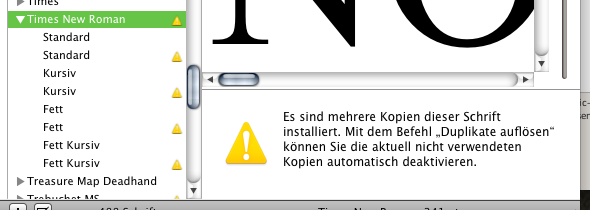
Zeilenhöhe Times New Roman vs. Doulos SIL
Die TNR einfach durch die Doulos zu ersetzten hab ich grad kurz versucht, das fällt aber auf, weil die TNR ein g mit Kringel (hat das nen »richtigen« Namen?) hat und die Doulos zwei Versionen einmal mit Kringel einmal normal und Word sich in dem Fall für das ohne Kringel entscheidet. Das gefällt mir nicht, ich weiß aber auch nicht, wie ich das ändern kann …
Ich hab mir nun doch mal diese Doulos runtergeladen.
Da gibt es ja nur einen Schnitt! Nicht mal eine Kursive. :o
Wegen des g: Hoffen wir mal, dass es an den FontCaches liegt. Hier bei mir wird jedenfalls auch in Word2008 das g mit geschlossener Schleife verwendet. Dein offenes g steckt tief in den Glyphvarianten der Schrift und sollte standardmässig nicht verwendet werden. Wie sieht es bei dir eigentlich mit dem a aus? Da gibt es in der Doulos eine "einstöckige" Variante.
Wenn du die Doulos Compact verwendest, verhält sie sich beim Zeilenabstand von ganz alleine wie die TNR.
Ja das mit a ist auch einstöckig, also nicht so wie das, was die Forenschrift hat…
Das die Doulos nur einen Schnitt hat ist auch doof. Ich werde das wohl so machen, dass ich die Times nutze und bei Bedarf die Zeichen aus der Doulos hinzunehme. Ligaturen könnte ich ja über ein Skript suchen und ersetzen lassen oder? Dabei: Kennt jemand eine gute Seite die die Makro-Programmierung erklärt? (Hab mich damit noch überhaupt nicht beschäftigt, aber die Frage passt hier grad… ICh kann aber HTML, PHP, CSS und Java; bin also nicht unbeleckt, was programmieren angeht)
Vielen Dank für den Tip mit der Kompakten! Läuft die auch schmaler als die normale SIL und genauso wie die TNR, weißt du das?
Edit/Nachtrag: Bei der kompakten wird ebenfalls das einstöckige a und das offene g benutzt (von Word, bei Pages ist alles normal und in der Schriftsammlung auch)
Seltsam. Aber bei solchen Fehlern würde ich gefühlsmässig darauf tippen, dass die mit Löschen der FontCaches weg sind.
Vielen Dank für den Tip mit der Kompakten! Läuft die auch schmaler als die normale SIL und genauso wie die TNR, weißt du das?
Auf der offiziellen Downloadseite steht, dass bei der Compact nur der Zeilenabstand reduziert wurde, sonst nix:
Dass dem so ist, kannst du ja auch leicht überprüfen, wenn du zwei Absätze mit Text (einmal "normal", einmal "compact") vergleichst. Die Zeilen laufen absolut identisch.
Ich könnte die Duplikate auflösen lassen, soweit ich weiß waren sie das vor dem ganzen Problem eh. Aber nach dem Motto never touch a running system bin ich unsicher, ob ich was machen soll…?
Könnte ich die Schriften auch ganz löschen, irgendwie? (Die Versionen siehe in einem vorherigen Post)
Ich hab grad rausgefunden, dass das mit den Glyphvarianten für a und g ind WOrd daran lag, dass Ligaturen aktiv waren. Sind die Ligaturen an, werden alle f-Ligaturen ordnungsgemäß benutzt aber eben auch das einstckige a und das Schleifen-g, sind die Ligaturen aus, wird keine Ligatur angezeigt und die normalen as und gs benutzt. Seltsam.
Mir bleibt also nichts außer suchen und ersetzen...
Komisch.
Die anderen Times' sollten eigentlich nicht mehr da sein.
Hast du mit FEX nur die Caches gelöscht oder auch die Funktion "System Fonts-Ordner aufräumen" betätigt?
Ich könnte die Duplikate auflösen lassen, soweit ich weiß waren sie das vor dem ganzen Problem eh. Aber nach dem Motto never touch a running system bin ich unsicher, ob ich was machen soll…?
Oder liege ich da falsch und den Sammlungen passiert nix?
Das Problem mit den Ligaturen tritt allerdings nur in Word auf… Pages benutzt die Ligaturen und die »normalen« as bzw. gs. Naja, Word ist eben komisch. 8)
Ist aber nicht weiter schlimm, weil ich die Doulos je eh nicht nutzen werde, da sie keinen kursiven und keinen fetten Schnitt hat.